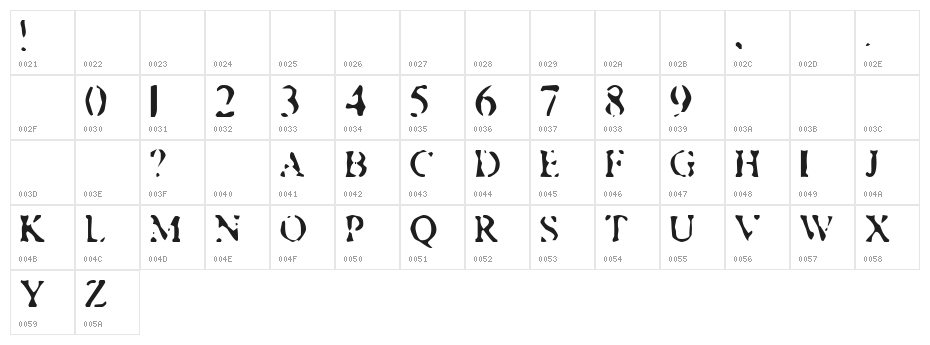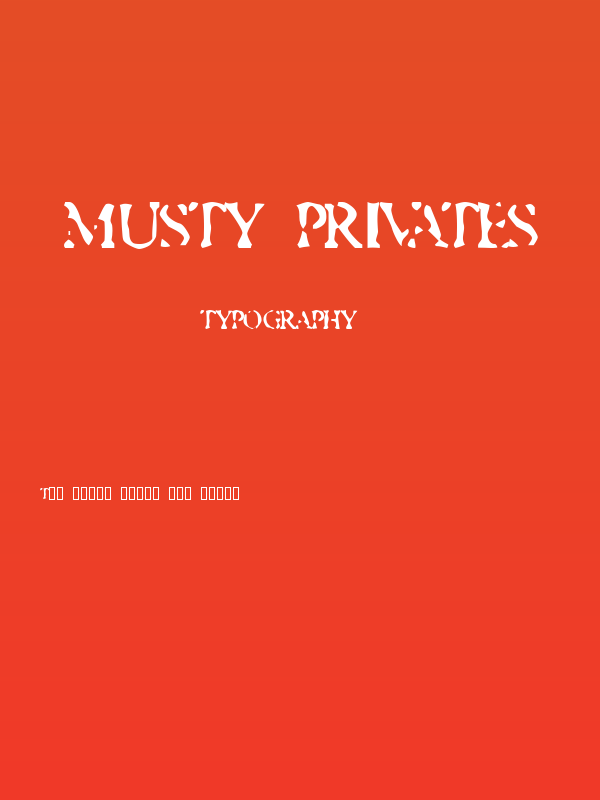
Musty Privates Font
✎ Capitals
| Gesamtstil | Modern, Avant-garde |
| Vorgeschlagene Projekte | Ideal for album covers, posters, branding projects, and any design that requires a bold and artistic statement. |